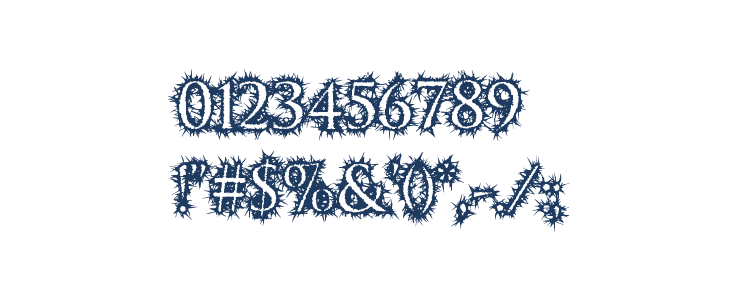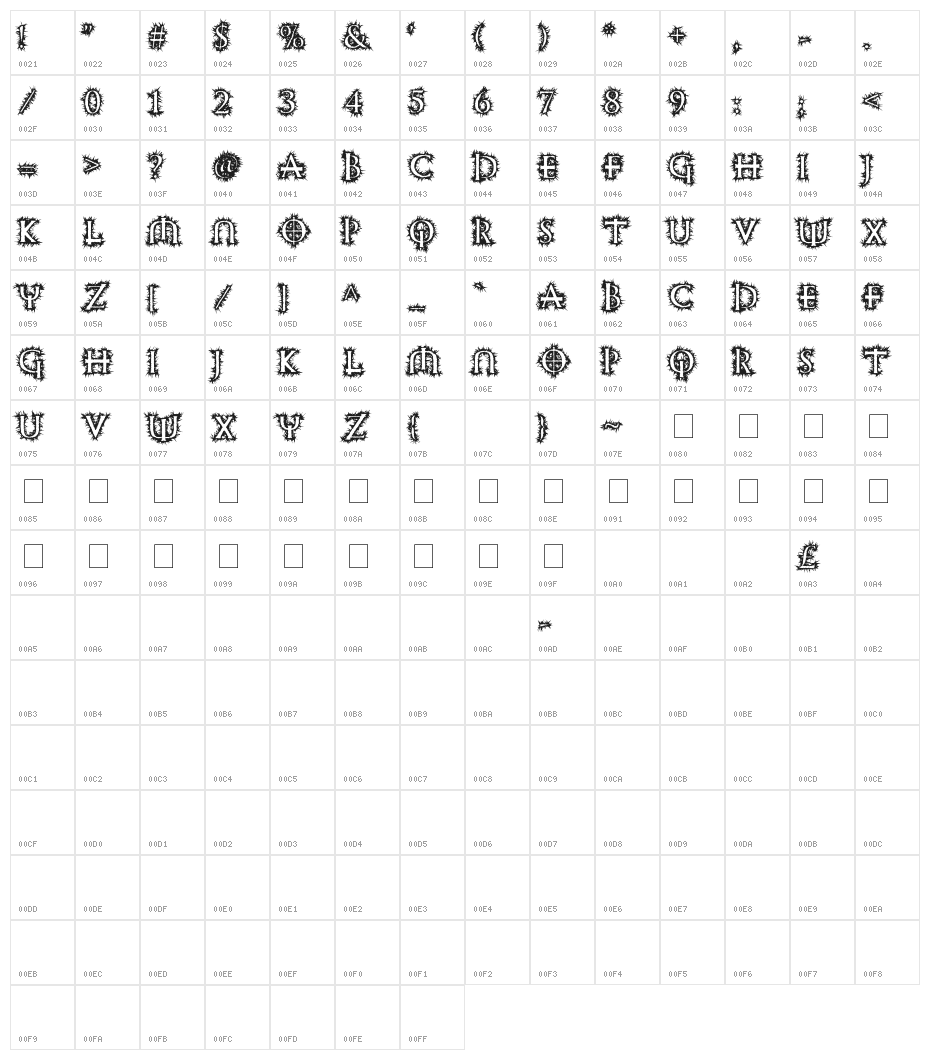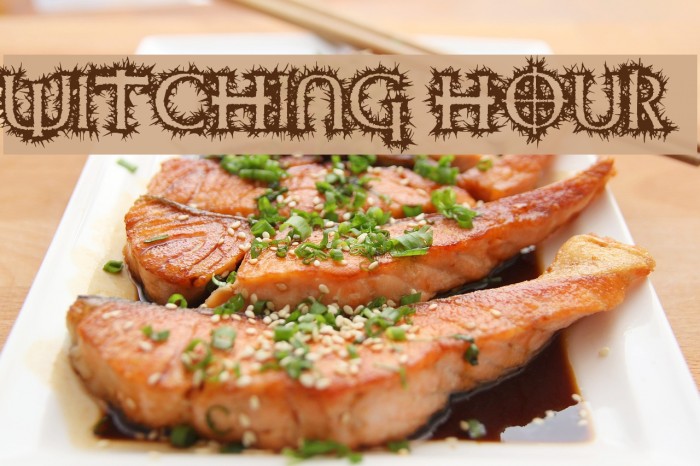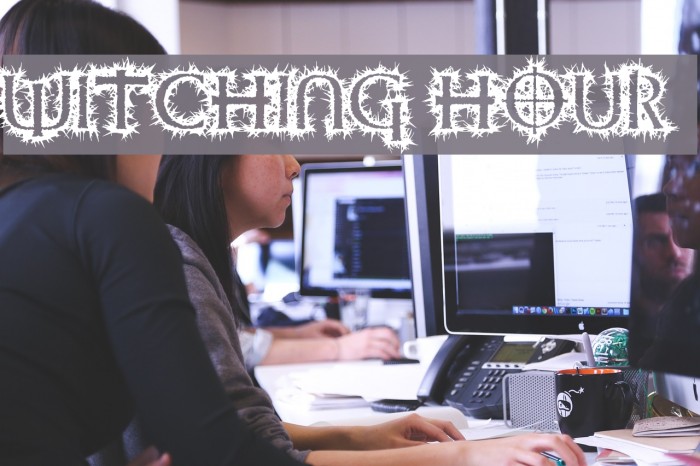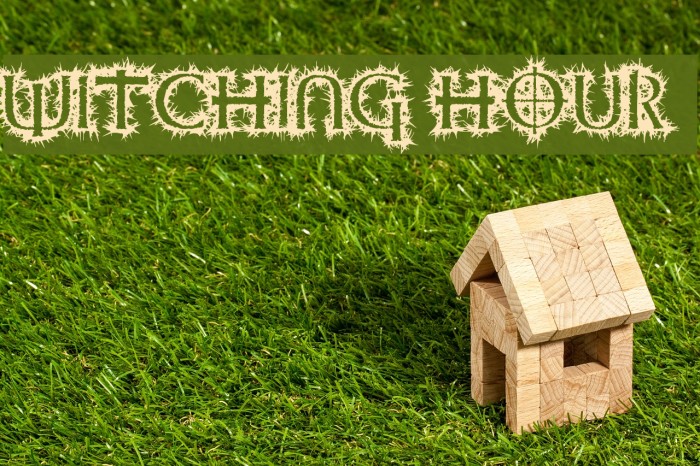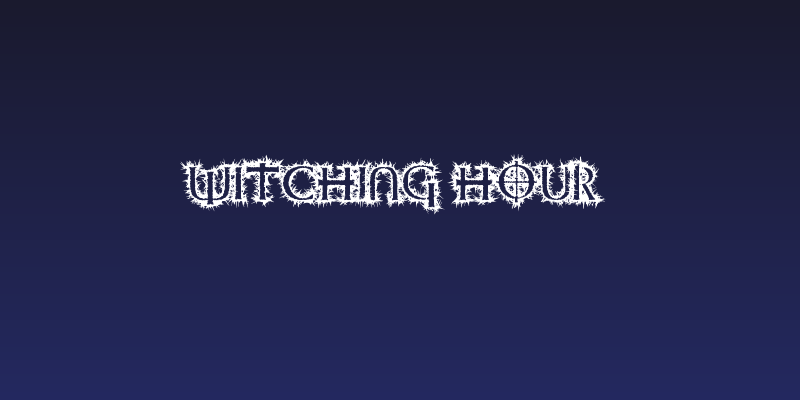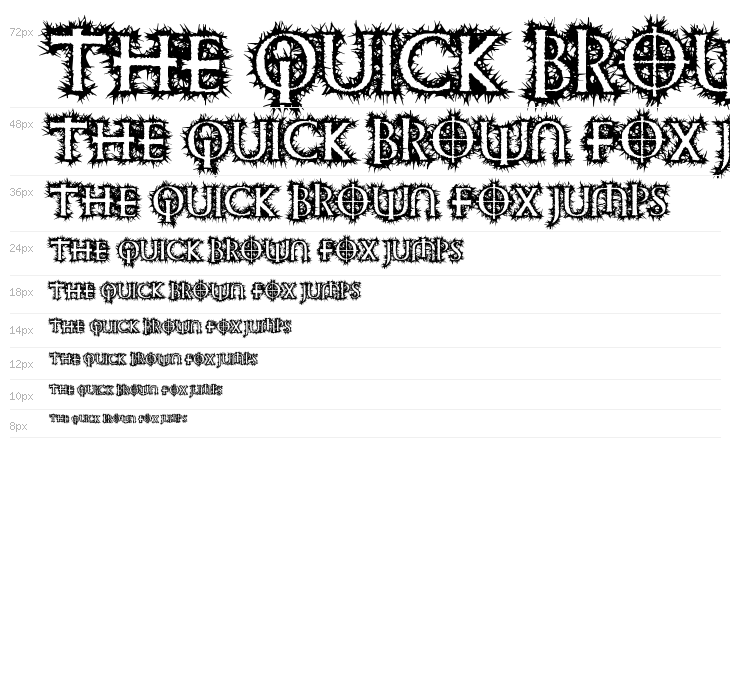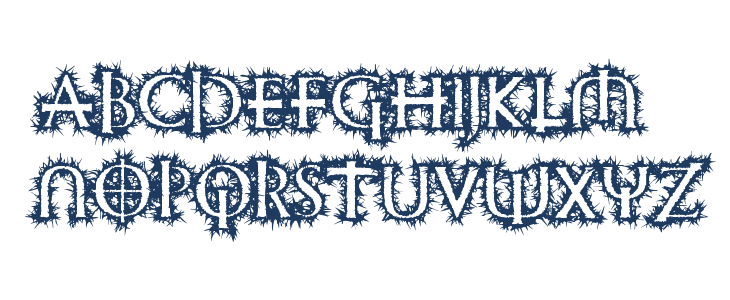
Witching Hour Font
| Stile generale | Gothic, Decorative |
| Caso d'uso | Headlines, Logos, Themed Events |
| Progetti proposti | Perfect for Halloween-themed designs, horror movie posters, fantasy book covers, or any project requiring a dark, mysterious aesthetic. |